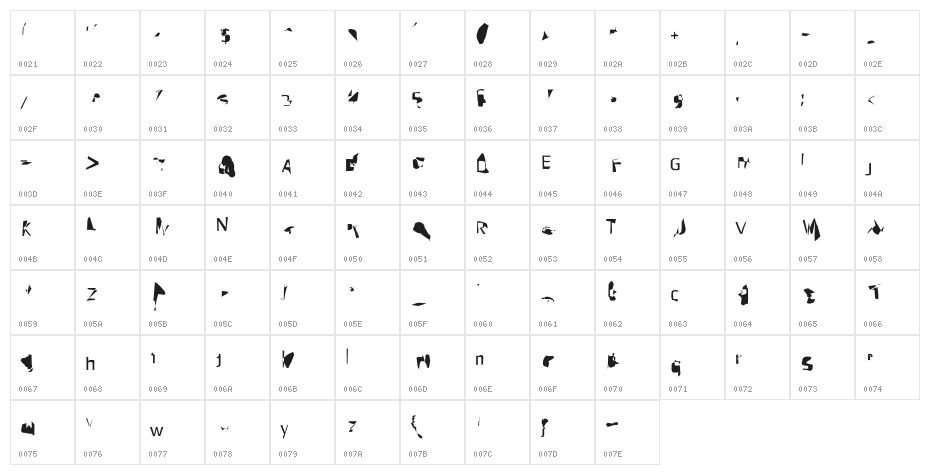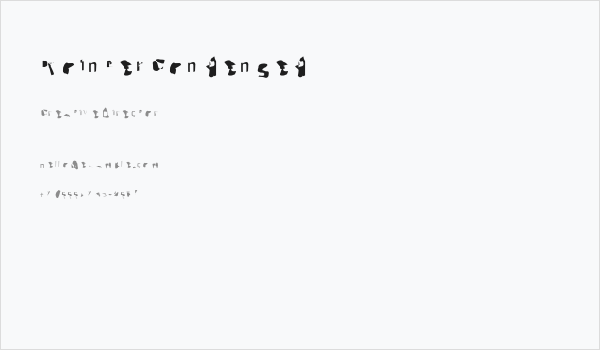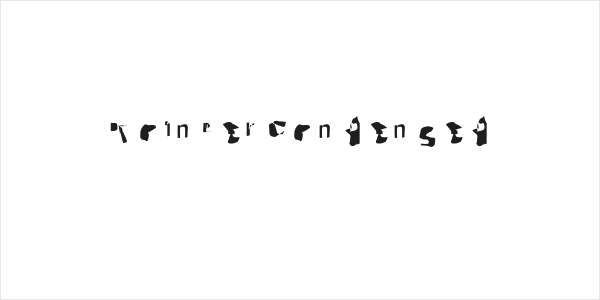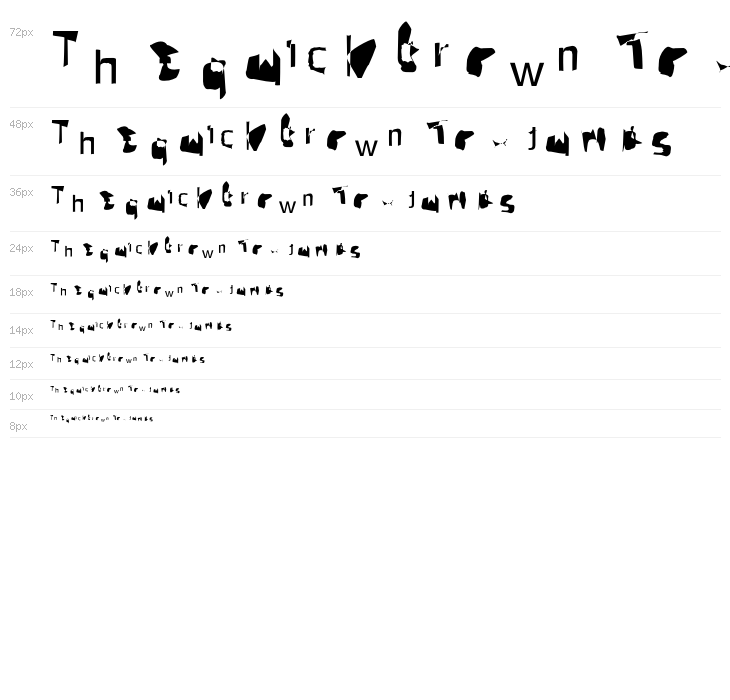
Pointer Condensed Font
| Gesamtstil | Modern, Edgy |
| Anwendungsfall | Logos, Headlines, Posters |
| Vorgeschlagene Projekte | Ideal for projects that require a strong visual impact, such as album covers, posters, or branding for edgy or alternative products. |